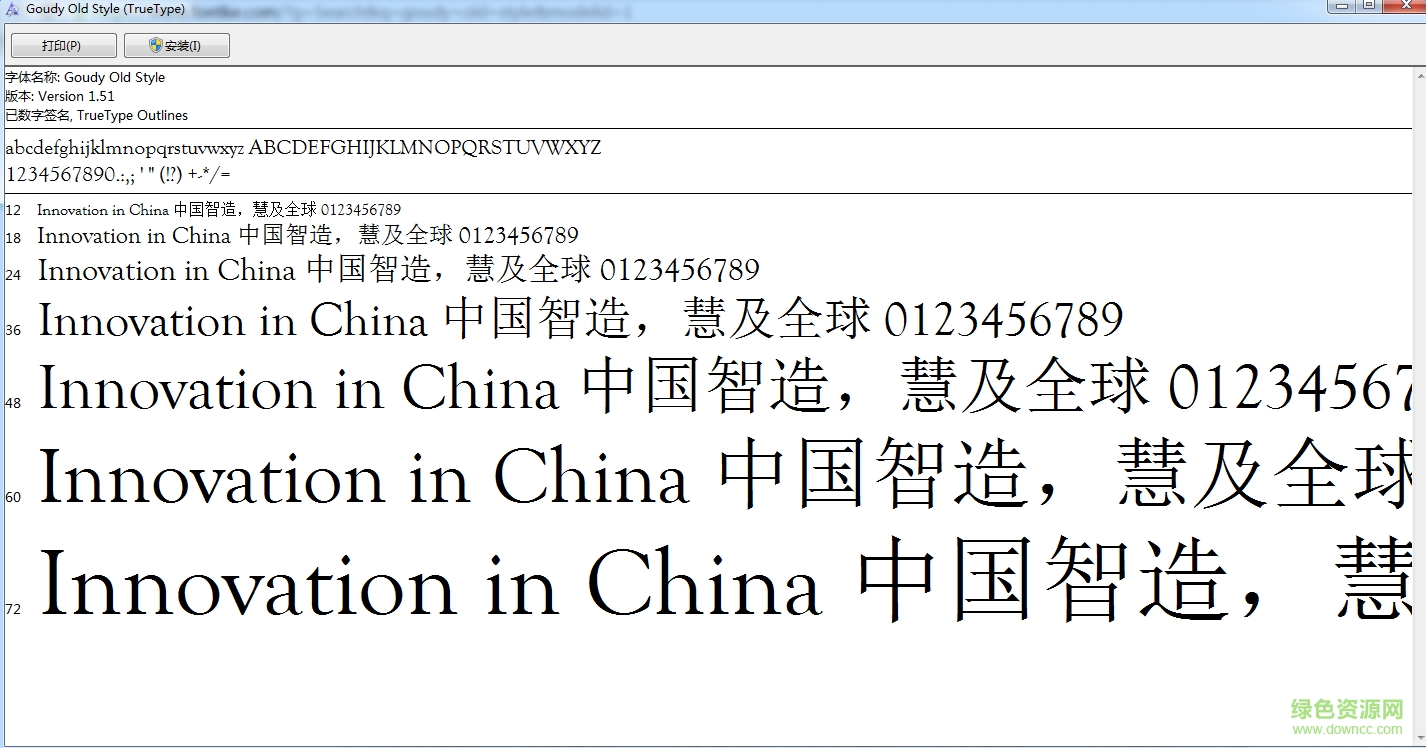
goudy old style字體是一款舊式風(fēng)格的襯線(xiàn)字體,字形精致優(yōu)美,風(fēng)格典雅,表現(xiàn)力強(qiáng),可應(yīng)用在創(chuàng)意設(shè)計(jì)、廣告設(shè)計(jì)、包裝裝飾、影視宣傳等方面!
在傳統(tǒng)的正文印刷中,普遍認(rèn)為襯線(xiàn)體能帶來(lái)更佳的可讀性(相比無(wú)襯線(xiàn)體),尤其是在大段落的文章中,襯線(xiàn)增加了閱讀時(shí)對(duì)字母的視覺(jué)參照。而無(wú)襯線(xiàn)體往往被用在標(biāo)題、較短的文字段落或者一些通俗讀物中。